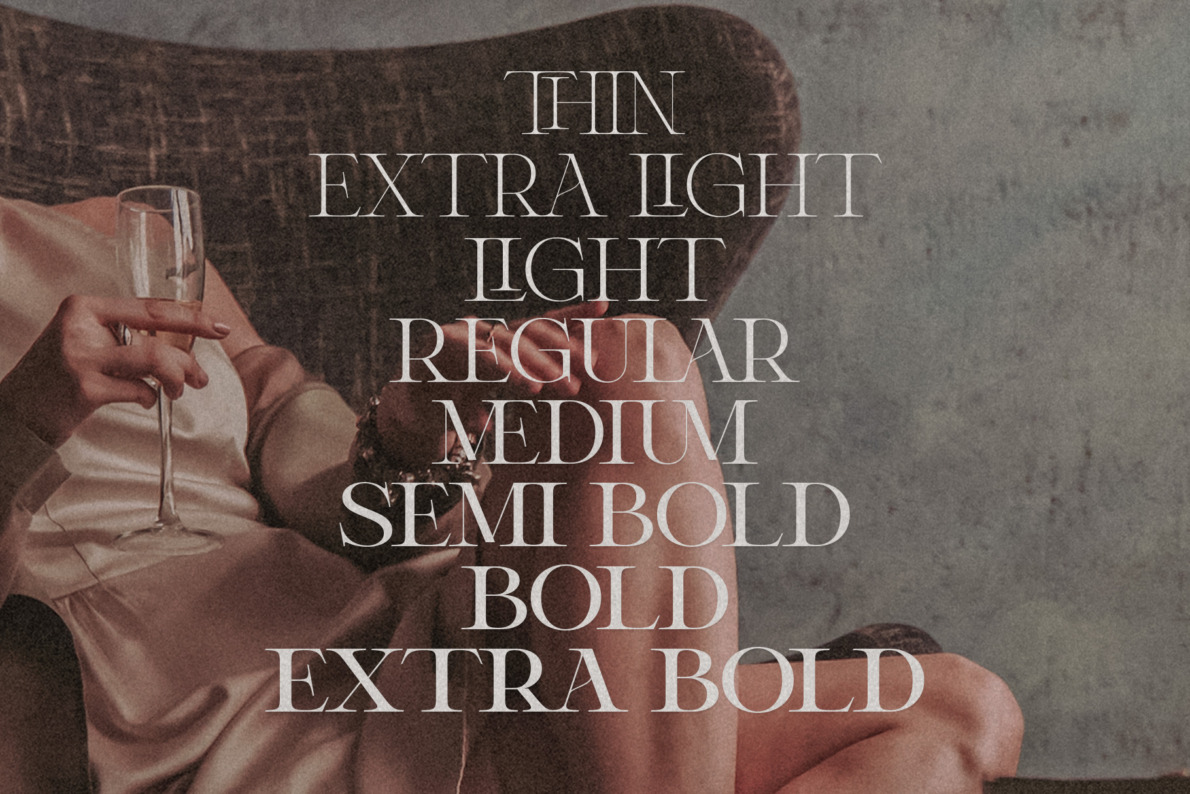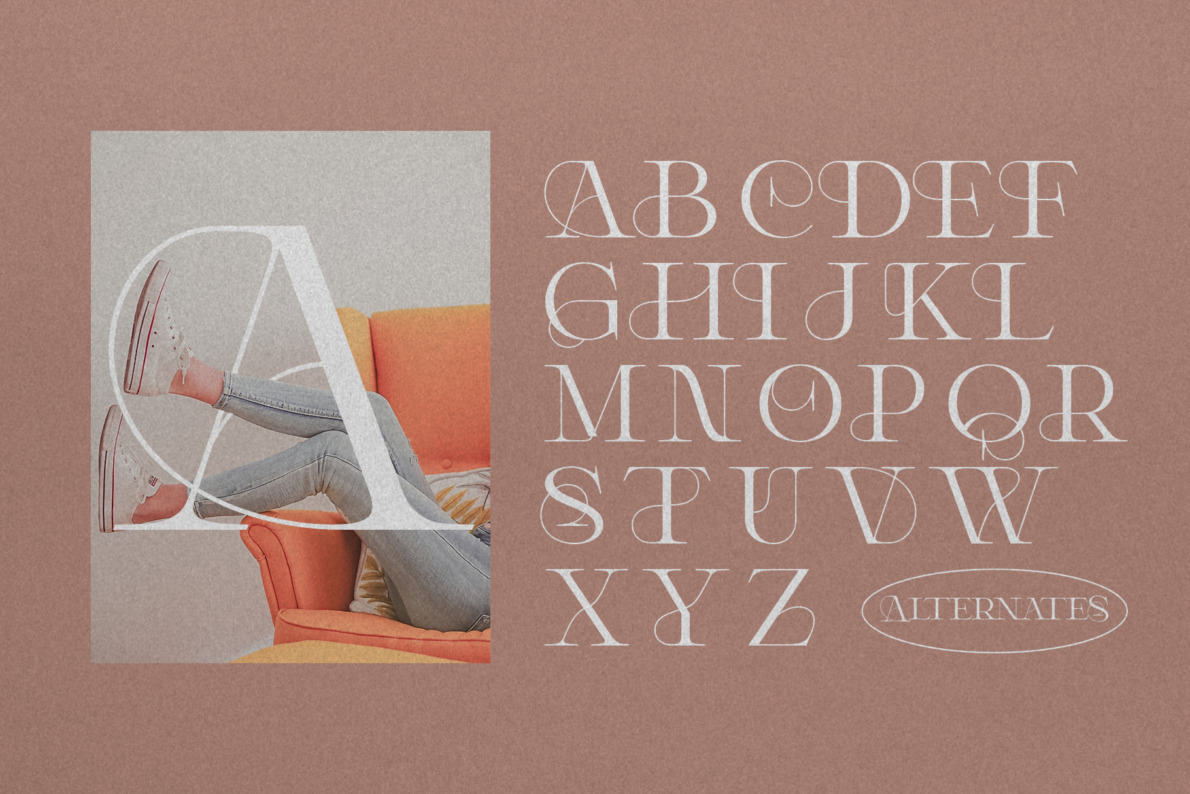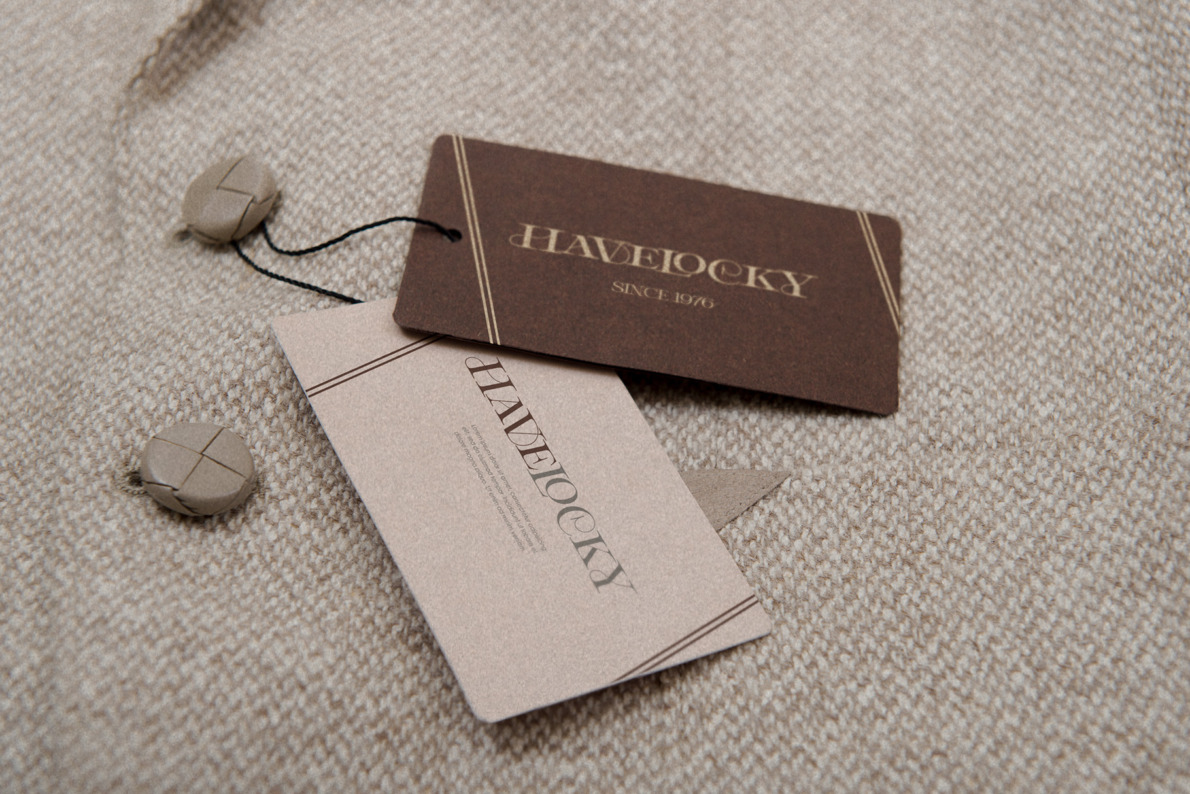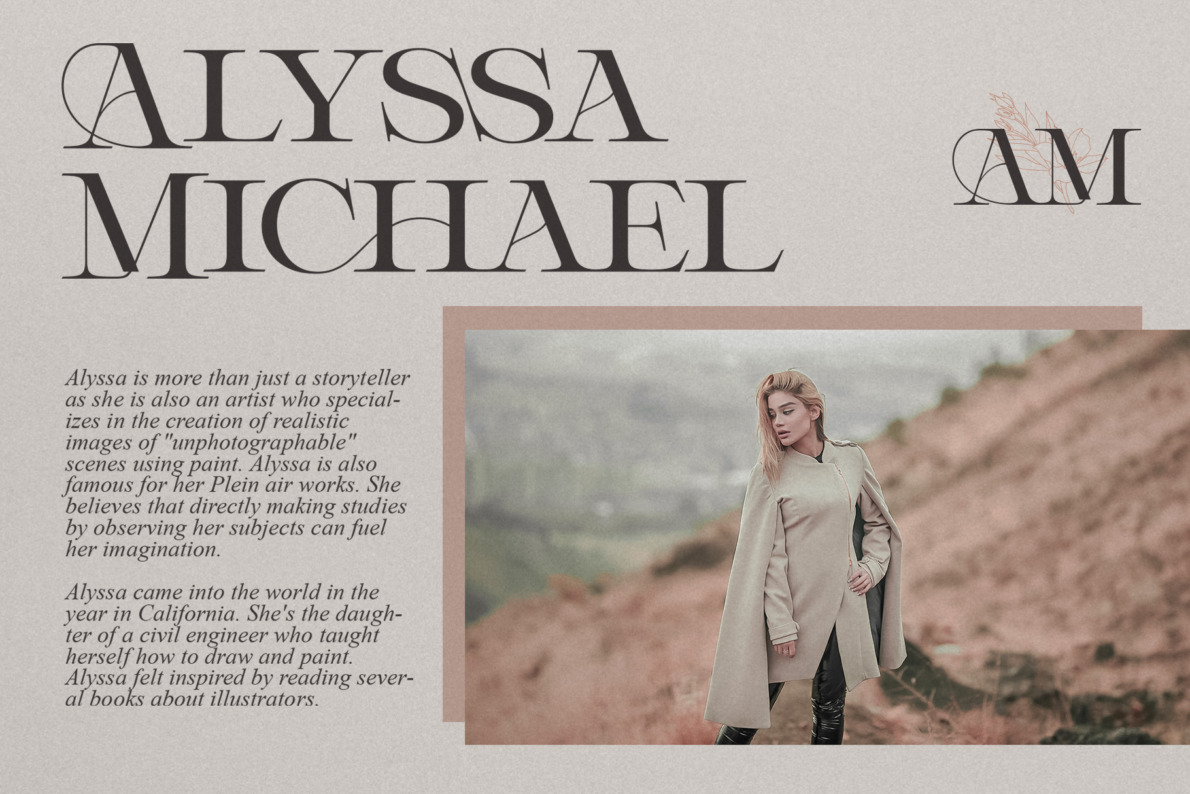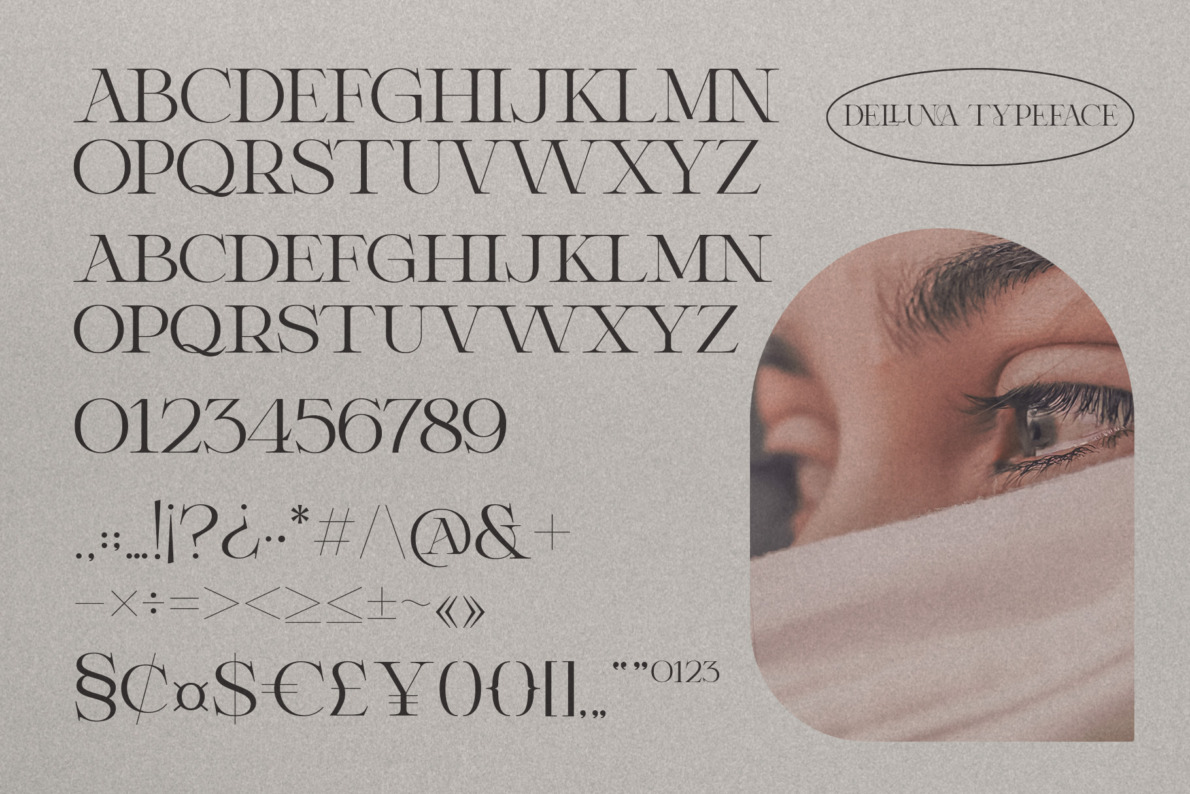
Giới thiệu về Font TF Delluna Việt hóa
TF Delluna Việt hóa là một font chữ có chân (serif) nổi bật với vẻ đẹp tinh tế, hiện đại và đầy cuốn hút. Với những đường nét được thiết kế sắc sảo, có sự pha trộn giữa nét cổ điển và hơi thở đương đại, Delluna toát lên phong thái sang trọng và đẳng cấp, rất phù hợp cho những thiết kế mang tính nghệ thuật cao và đòi hỏi sự ấn tượng.
Font này là lựa chọn lý tưởng để tạo nên sự độc đáo và chuyên nghiệp, đặc biệt là trong các lĩnh vực yêu cầu tính thẩm mỹ và sức hút:
- Thiết kế poster ca nhạc: Hoàn hảo để làm tiêu đề chính, tên nghệ sĩ hoặc các thông tin quan trọng trên poster quảng bá concert, festival âm nhạc, hoặc album mới. Delluna giúp poster trở nên nổi bật, nghệ thuật và thu hút sự chú ý của khán giả, gợi cảm giác về sự kiện âm nhạc chất lượng cao.
- Thiết kế thời trang: Lý tưởng cho các thương hiệu thời trang cao cấp, từ nhãn mác sản phẩm, lookbook, đến các chiến dịch quảng bá bộ sưu tập. Font này giúp truyền tải sự tinh tế, phong cách và đẳng cấp của trang phục, nâng tầm giá trị thương hiệu.
- Tạp chí và ấn phẩm nghệ thuật: Phù hợp cho các tiêu đề, bài viết, hoặc các phần nội dung cần sự sang trọng và cuốn hút trong các tạp chí về thời trang, nghệ thuật, hoặc lối sống.
Với TF Delluna Việt hóa, bạn có thể dễ dàng thổi hồn nghệ thuật, sự tinh tế và sang trọng vào các thiết kế, tạo ra những sản phẩm không chỉ đẹp mắt mà còn đầy cảm xúc và sức hút.
Font Việt hóa TF Delluna – Font ca nhạc, nhiều glyphs